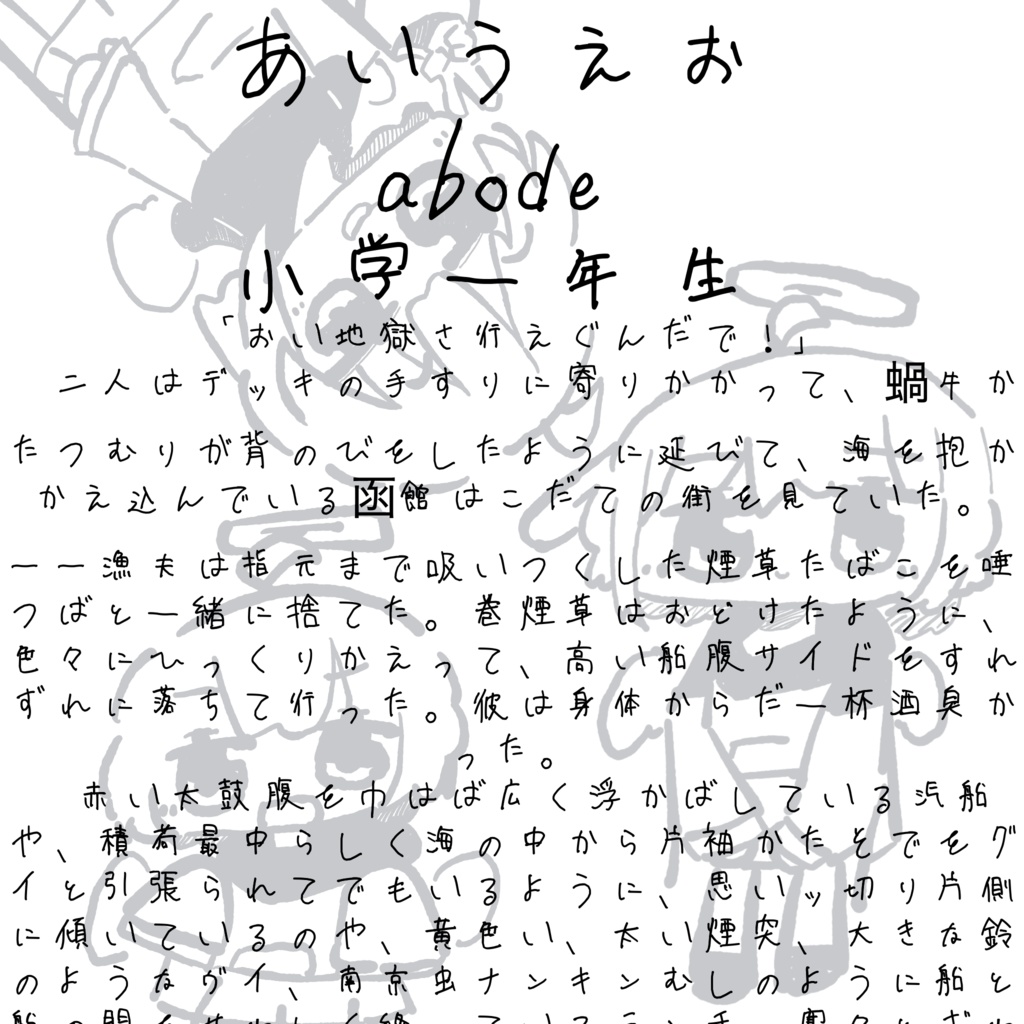
ハルヤゴッドクリエートグレートハルヤフォントダウンロード商品¥ 0無料ダウンロードHaruya2.zip (1.36 MB)Haruya2.zip「ギフトとして贈る」とは超グレートなフォントです! 多分、常用漢字はカバーしています ガタガタだけど、許してください 本来なら240万ですが、期間限定9999年99月99日まで無料です! フォントの形式わからなくてoftって拡張子ですが、あたしのiPadでは使えるので大丈夫です ノークレームノーリターン 値下げ❌ハルヤゴッドクリエートFANBOX開設中Tシャツ在庫なしグレートハルチャンTシャツハルヤゴッドクリエート¥ 1,0003Dモデル(その他)面が反転してるパンダハルヤゴッドクリエート¥ 0